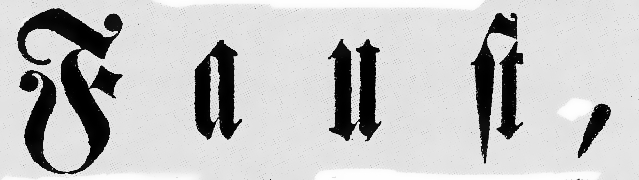
Suche eine Fraktur mit Schnörkeln
Ich suche diese Schriftart.
Speziell die ſt-Liguatur hat es mir angetan, aber auch der "Schnörkel" am F zur "Serife" oder "Tropfen nach oben" (Ich habe leider keine Ahnung von Fraktur) gefällt mir. Das Bild stammt ursprünglich aus der Wikipedia ( http://upload.wikimedia.org/wikipedia/commons/7/72/Braunschweig_Faust-Urauffuehrung_19_Jan_1829.jpg ) und ich habe hier eine verschlimmbesserte Version von der gesuchten Stelle hochgeladen.
Gibt es solch altertümliche Schriften für den PC? Wenn nicht würde mir auch ein Name oder ein weiteres Bild, gerne auch von ähnlichen Schriften weiterhelfen.
Die Freunde der gepflegten Fraktur hier im Forum können dir im speziellen vielleicht besser helfen, aber einen kleinen Überblick über gebrochene Schriften findest du auf jeden Fall hier und hier. Das Stichwort zum Suchen heißt ›Blackletter‹.
Die einschlägigen Quellen habe ich schon durchsucht, aber Fraktur ist ein für mich ziemlich unübersichtliches Feld, wohl weil es ähnlich fassettenreich wie die Antiqua ist aber kaum noch in gebrauch und mich quasi unbekannt ist.
"Schnörkel" ist wohl auch falsch, verspielt trifft die Sache wohl eher. Ich meine nicht soetwas hier: http://www.fontsquirrel.com/fonts/PlainBlack sondern eine wie man im Bild sieht sehr konservative, mittelschwere Variante.
Diese kreisrunden Tropfen sind typisch für klassizistische Schriften. Bei Frakturen kommen sie jedoch weniger vor, typisch sind sie für die sogenannten Kanzleien.
Die einzige Fraktur, die ich kenne, die solche Tropfen vermehrt enthält, ist die Walbaum-Fraktur. Beim F hat sie aber gerade keine.
Den Schriftmusterprospekt von Dipl.-Ing. Helzel hast Du durchgesehen? Dort findest Du auch einige Kanzleien.
Leider bin ich dort auf nichts wirklich vergleichbares gestoßen. Aber vielleicht bin ich auch nur zu pingelig, :-)